En bortglemt samling av designtidsskrifter, skrifttyper i metall og tre samt sjeldne skriftkataloger på Kunsthøgskolen i Oslo har fått nytt liv. Skolen tar i bruk gammel boktrykkteknikk og har skapt økt interesse for historien til norsk grafisk design. Deler av denne samlingen stilles ut fram til 31. desember 2013.
En gang på 1960-tallet ble dette materialet stuet bort på loftet i skolens lokaler i Ullevålsveien. For noen år tilbake ble det hentet fram igjen og tatt i bruk av studenter og andre. Nå er det på plass i de nye lokalene i Seilduksfabrikken på Grünerløkka, og det brukes aktivt i skolens undervisning.
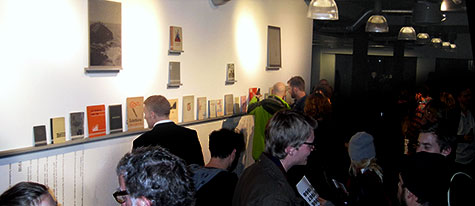
Det var stort frammøte på vernissagen til utstillingen av KHiOs typografiarkiv.
Det er internasjonalt en økende interesse for den gamle boktrykkteknikken med løse typer og høytrykk. På Kunsthøgskolen i Oslo er det førsteamanuensis Maziar Raein som har mye av æren for å ha satt i stand utstyret og fått det inn i undervisningen.
Utstillingen har tittelen «En form for historie». I den gratis katalogen man kan ta med seg heter det:
For gjennom historien kan vi se oss selv i et kontinuum. Man kan posisjonere seg, ta stilling til egen praksis og sine egne valg som utøver. Slik skapes en kritikalitet. Vi oppfatter kritikaliteten som en måte å beskrive og kontekstualisere, det handler om å forstå og å tilegne seg kunnskap – noe som er en vesentlig del av en konstruktiv grafisk design-praksis. Historien blir slik viktig som en måte å begripe feltet og oppnå innovasjon.
Katalogen inneholder artikler og intervjuer med norske og internasjonale designere som har et aktivt forhold til fagets historie. Her problematiseres betydningen av den grafiske designhistorien. En gjennomgående innfallsvinkel i artiklene er at kunnskap om historien skal brukes til å skape noe nytt i dag, ikke til kopiering.
Nær hundre mennesker var til stede ved utstillingsåpningen 14. november i Grafills lokaler i Rosenkrantz gate 21 i Oslo. En del objekter fra samlingen er utstilt, sammen med mange interessante sitater fra den grafiske bransjens aktører, organisert i en kronologisk rekkefølge. I et bakrom kjøres en kontinuerlig video der man ser det blir bladd i de mest verdifulle skriftkatalogene i typografiarkivets eie.
Et av premissene for utstillingen er at norsk grafisk designhistorie er svak, at den i liten grad er blitt avdekket, og derfor i liten grad er kjent. - Norge har hatt en treg utvikling på dette feltet, og jeg innså at jeg vet mye om hva som har skjedd internasjonalt, men ingenting om hva som har skjedd her til lands, sier den prisbelønte norske grafiske designeren Aslak Gurholt Rønsen i materialet til utstillingen. Da Maziar Raein kom til Norge ble han møtt av oppfatningen om at landet har ingen grafisk historie.
Det er riktig at Norge kom seint i gang med boktrykking. De neste 150 åra var Norge underlagt Danmark og veksten i antall trykkerier og fagutøvere var derfor svak. Men etter min mening har bransjen fra 1820-tallet til i dag fulgt utviklingen i Europa både teknisk og estetisk på de fleste felt. Vi har gjennomgått de sentrale stilperiodene som f.eks. jugend og funksjonalisme, og våre beste trykkerier har investert i det siste tekniske utstyret. Grafiske kunstnere, tegnere og reklamefolk, som etter hvert kalte seg designere, har laget verdifulle arbeider etter cirka år 1900. Blant disse kan nevnes Thorolf Holmboe, Harald Damsleth og Peter Haars, som favner hele det forrige århundret.
Mye av denne historien er blitt dokumentert og analysert. Som eksempler kan nevnes Samlagets mange små bøker om norsk grafisk design, utgitt på 1980-tallet; Veitebergs bok Den norske plakaten (1998); Bokens ansikt (2002); og mine artikler om norsk boktrykkhistorie, samlet her på nettstedet Typografi i Norge. Men fortsatt er mye ugjort.
Kanskje problemet heller har vært at våre undervisningsinstitusjoner lenge i for liten grad har benyttet seg av den norske designhistorien. Fokus har vært på de (for interesserte studenter og utøvere) velkjente internasjonale milepælene og på sentrale aktører som bl.a. Morris, Tschichold og Morison. (Jeg vet at unntak finnes.)
Nå er det tydeligvis en endring på gang, og typografiarkivet på KHiO og utstillingen «En form for historie» bidrar til økt interesse for historien.